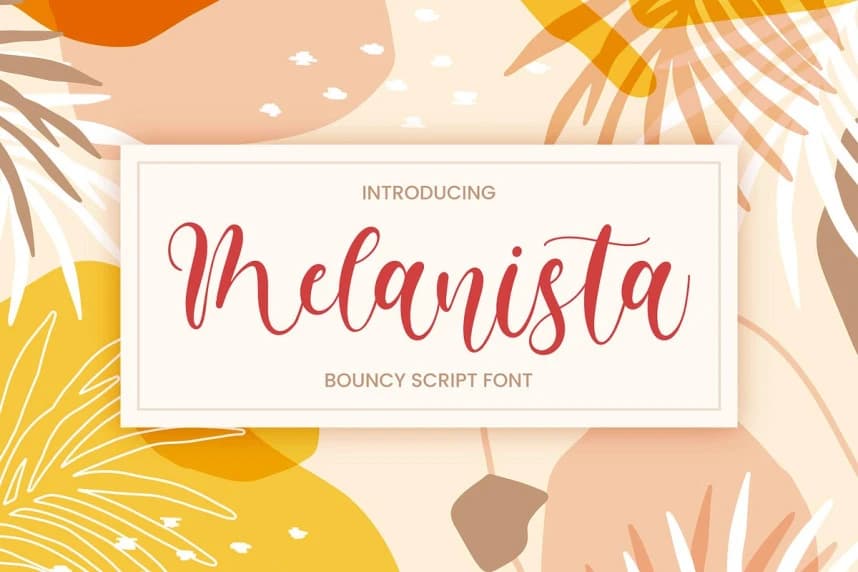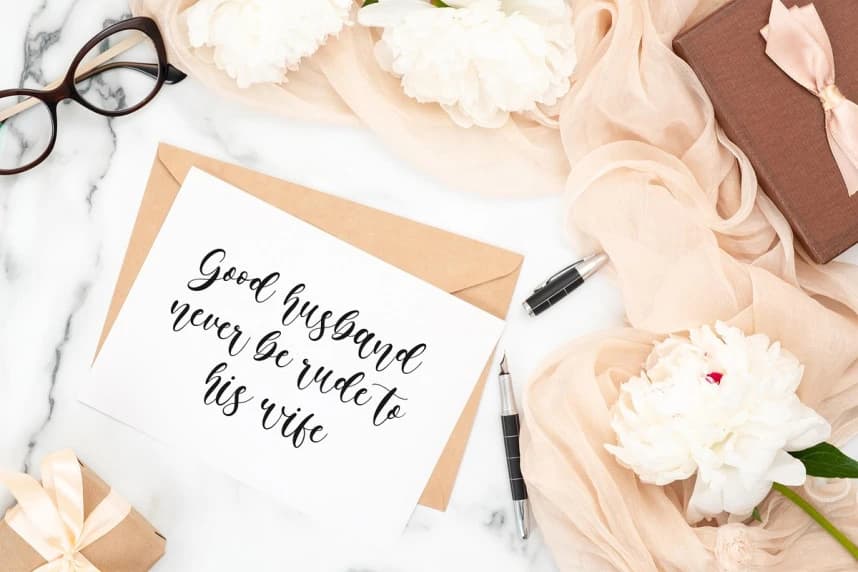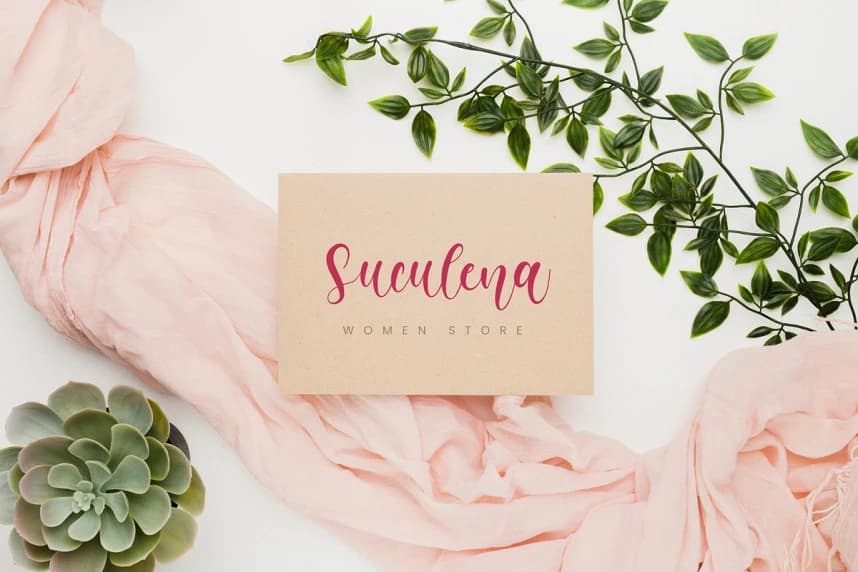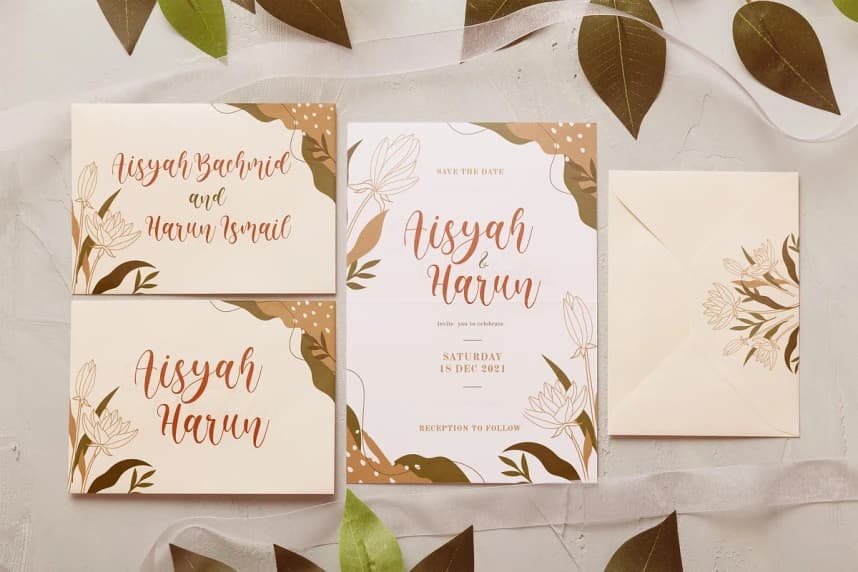
Melanista Script Font
Melanista Script Font, her yaratıcı tasarım için mükemmeldir. Bu el yapımı yazı tipi tasarımınıza her bir ayrıntıda güzel doğal bir dokunuş katacak. Davetiye, logo, kitap kapağı, el işi veya herhangi bir tasarım amacı için mükemmeldir.
Melanista Script Font, her türlü yaratıcı tasarım için mükemmel. Bu el yapımı yazı tipi tasarımınıza her detaya güzel doğal bir dokunuş katacak. Her türlü tasarım projesi için idealdir: Davetiye, logo, kitap kapağı, el işi veya diğer tasarım amaçları.
Melanista Script
Melanista Script Melanista Regular